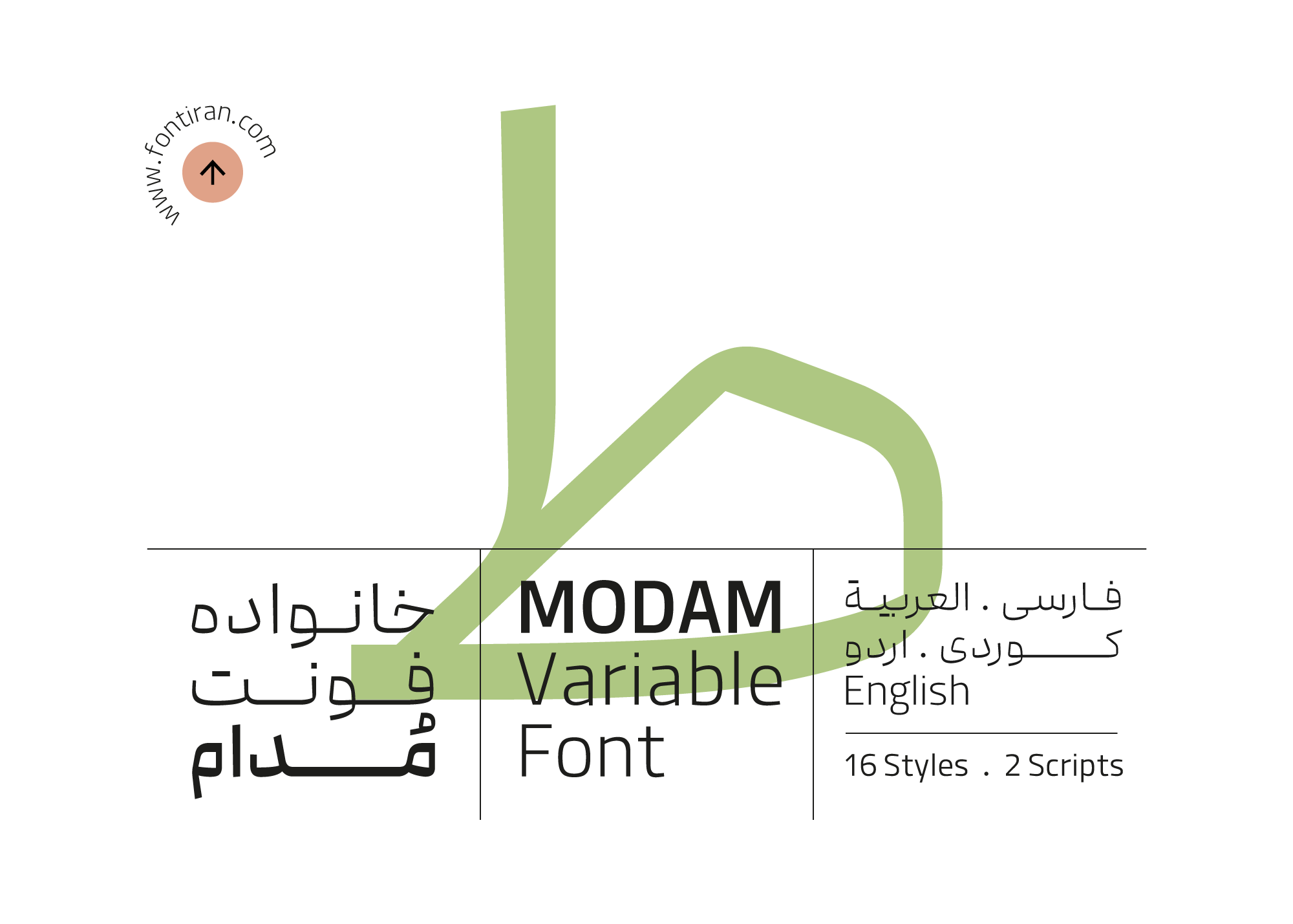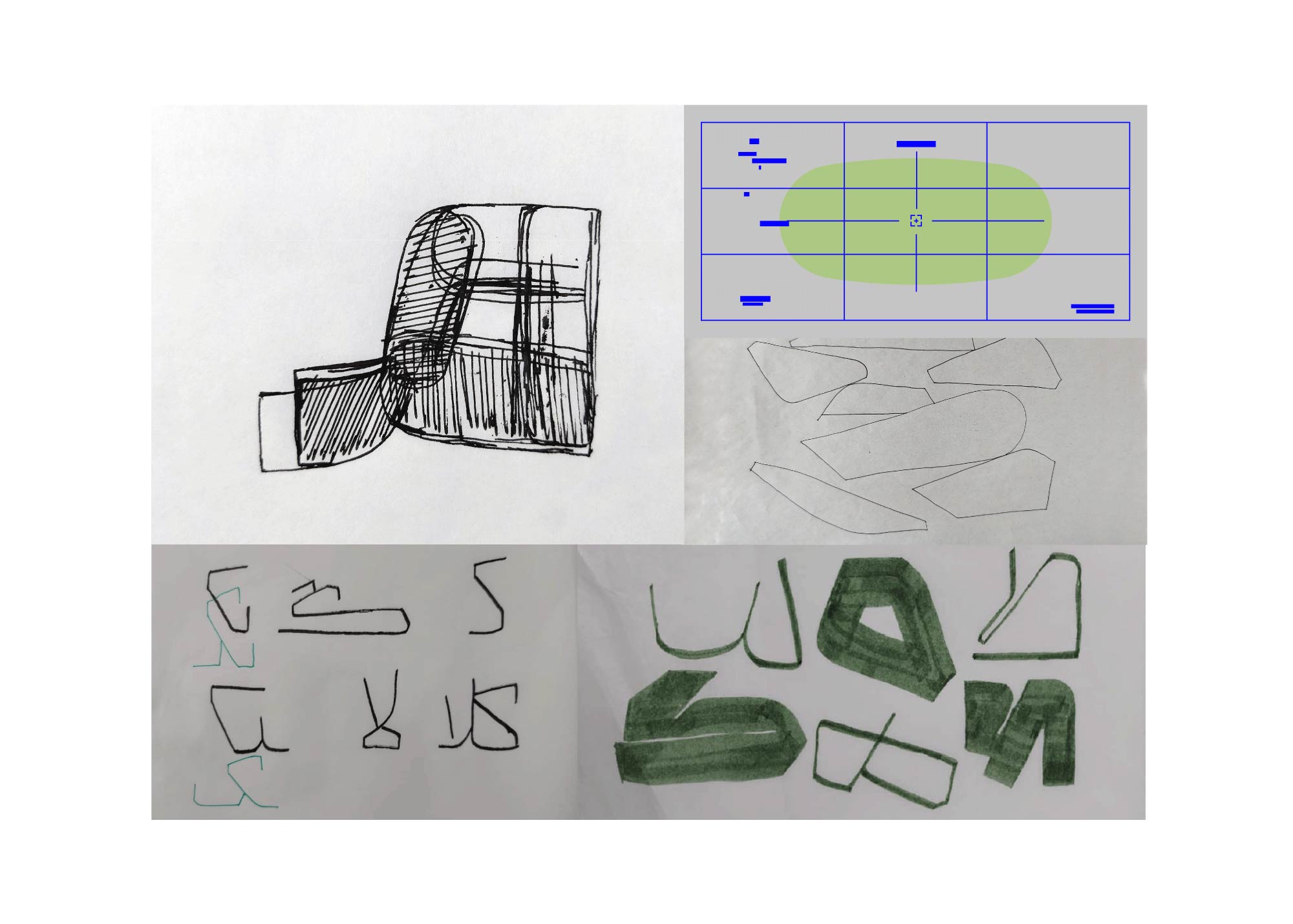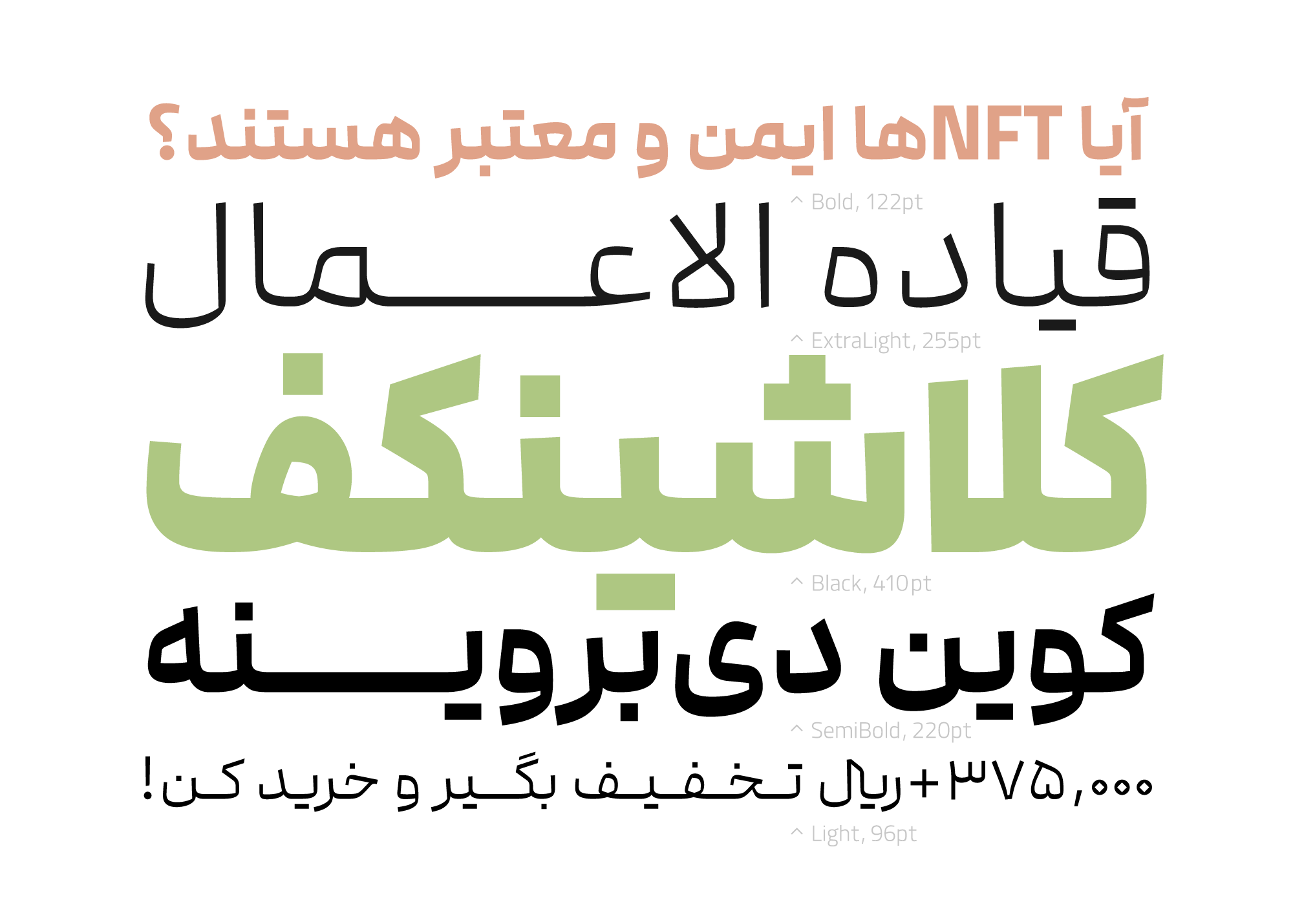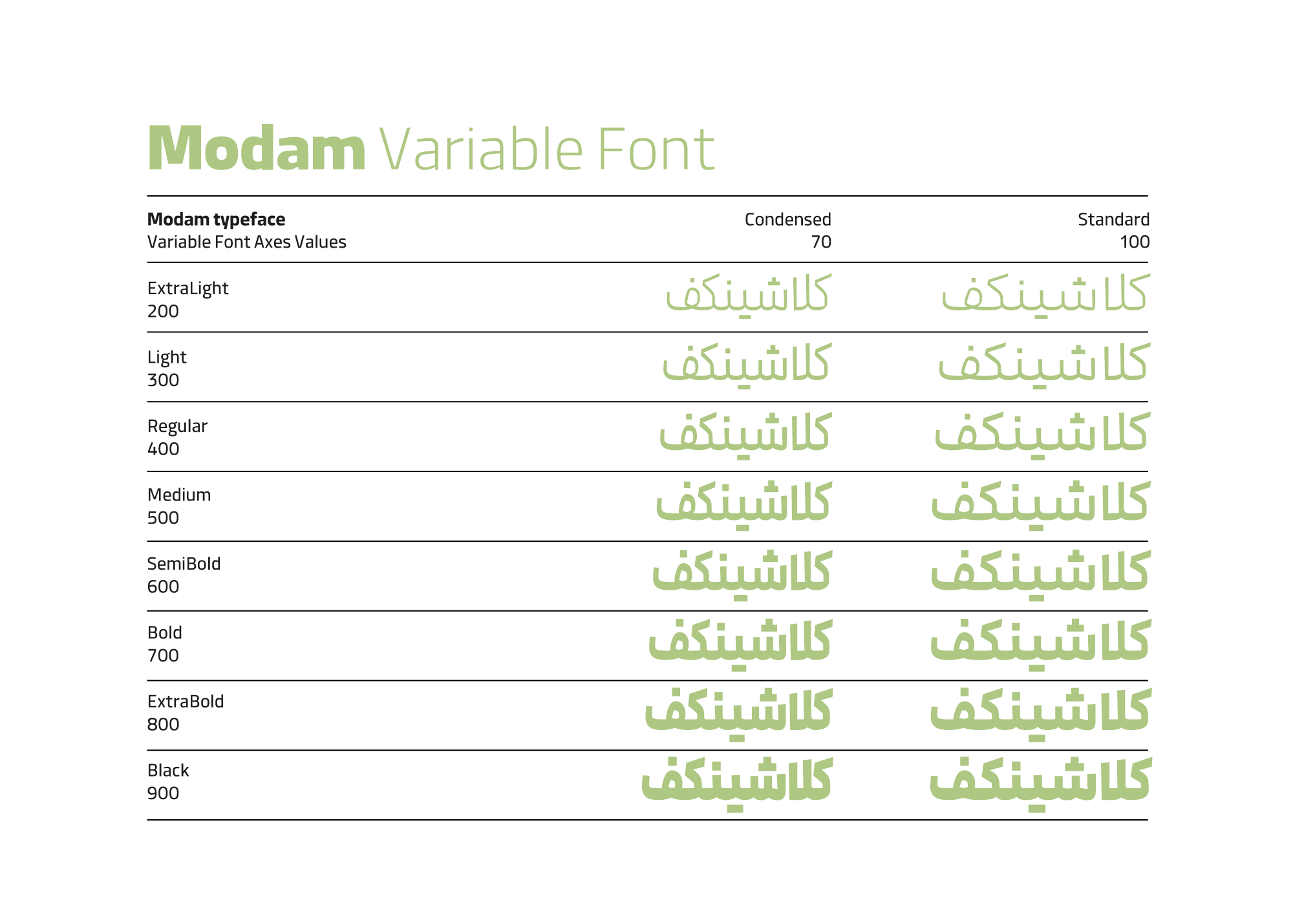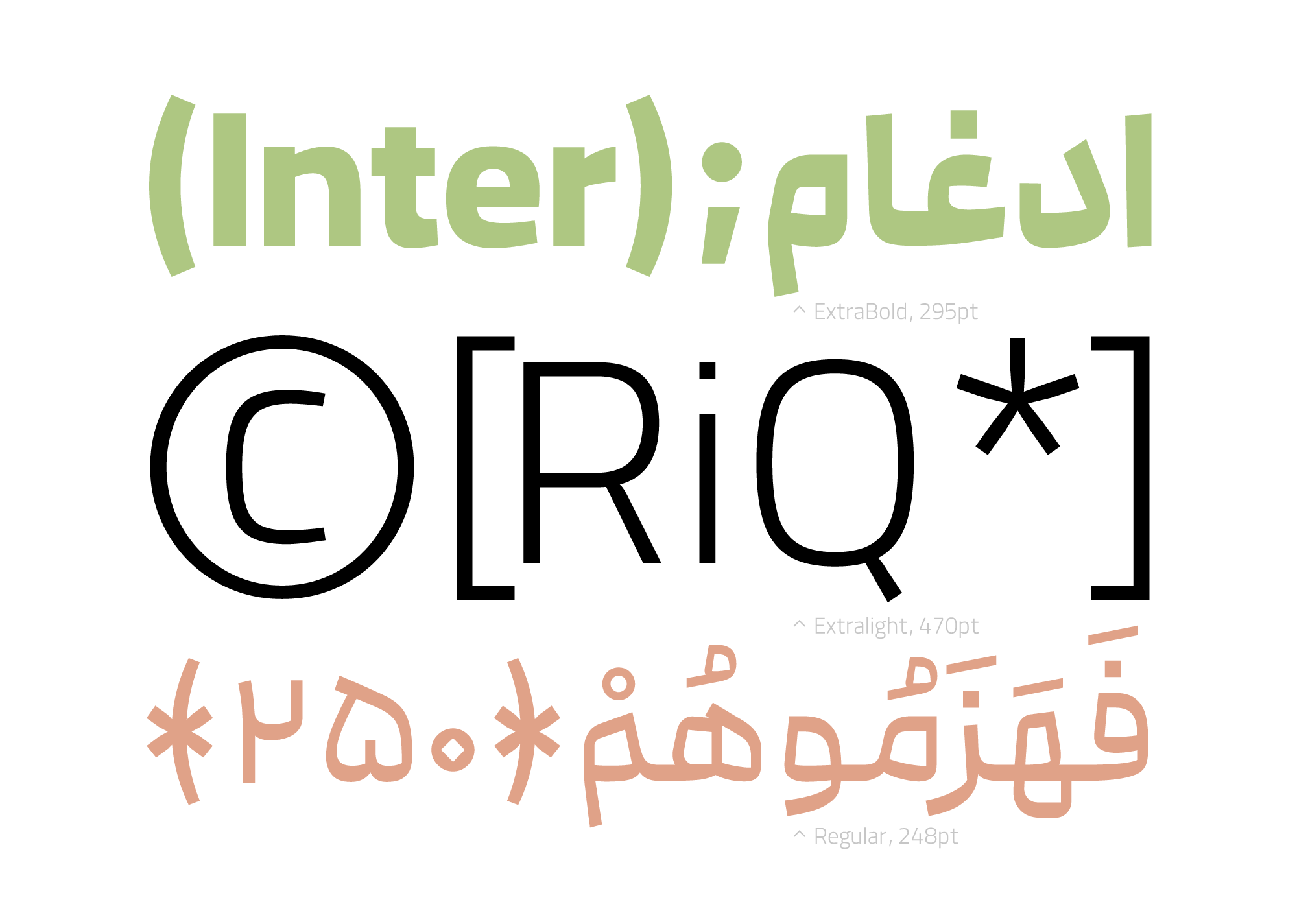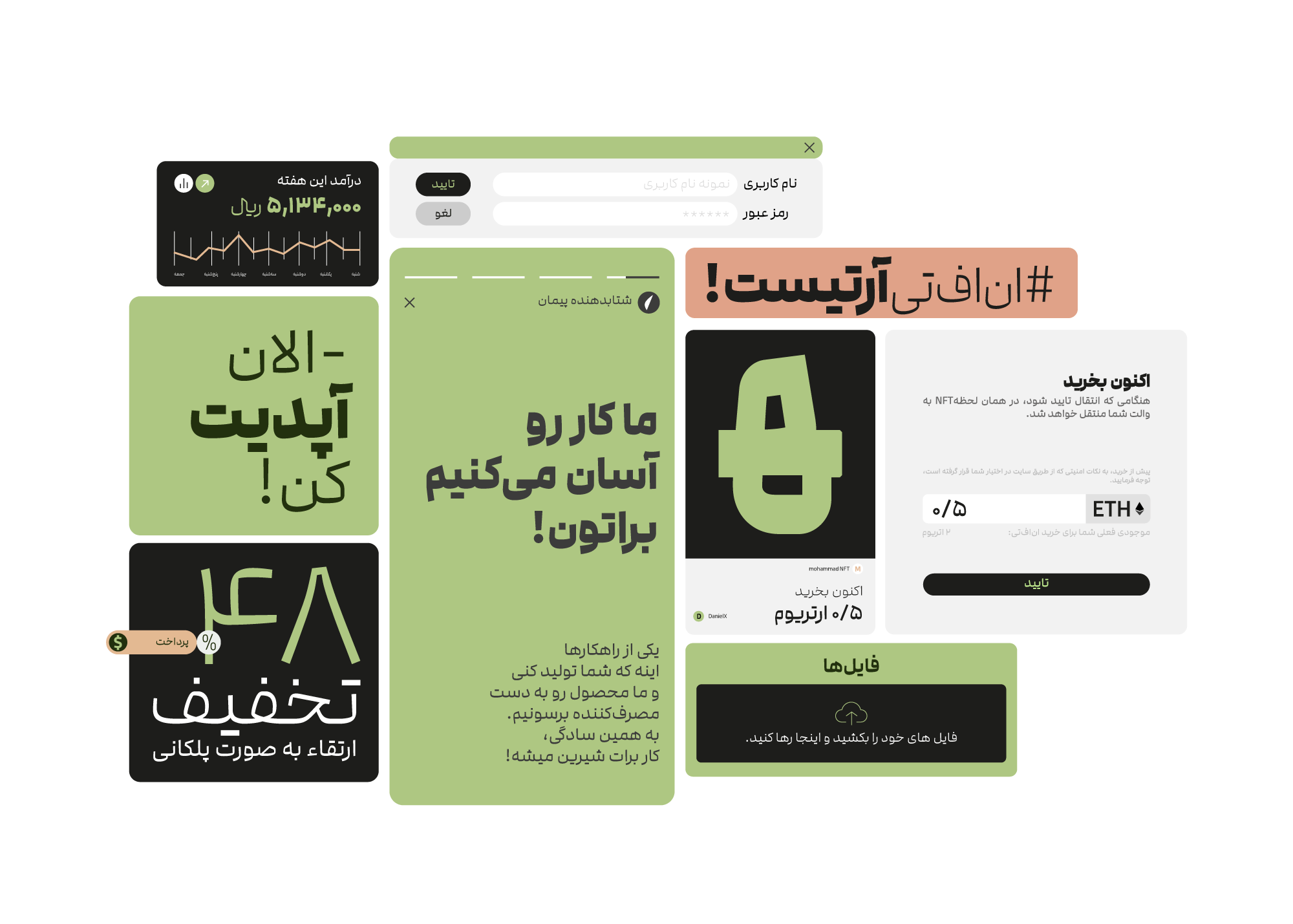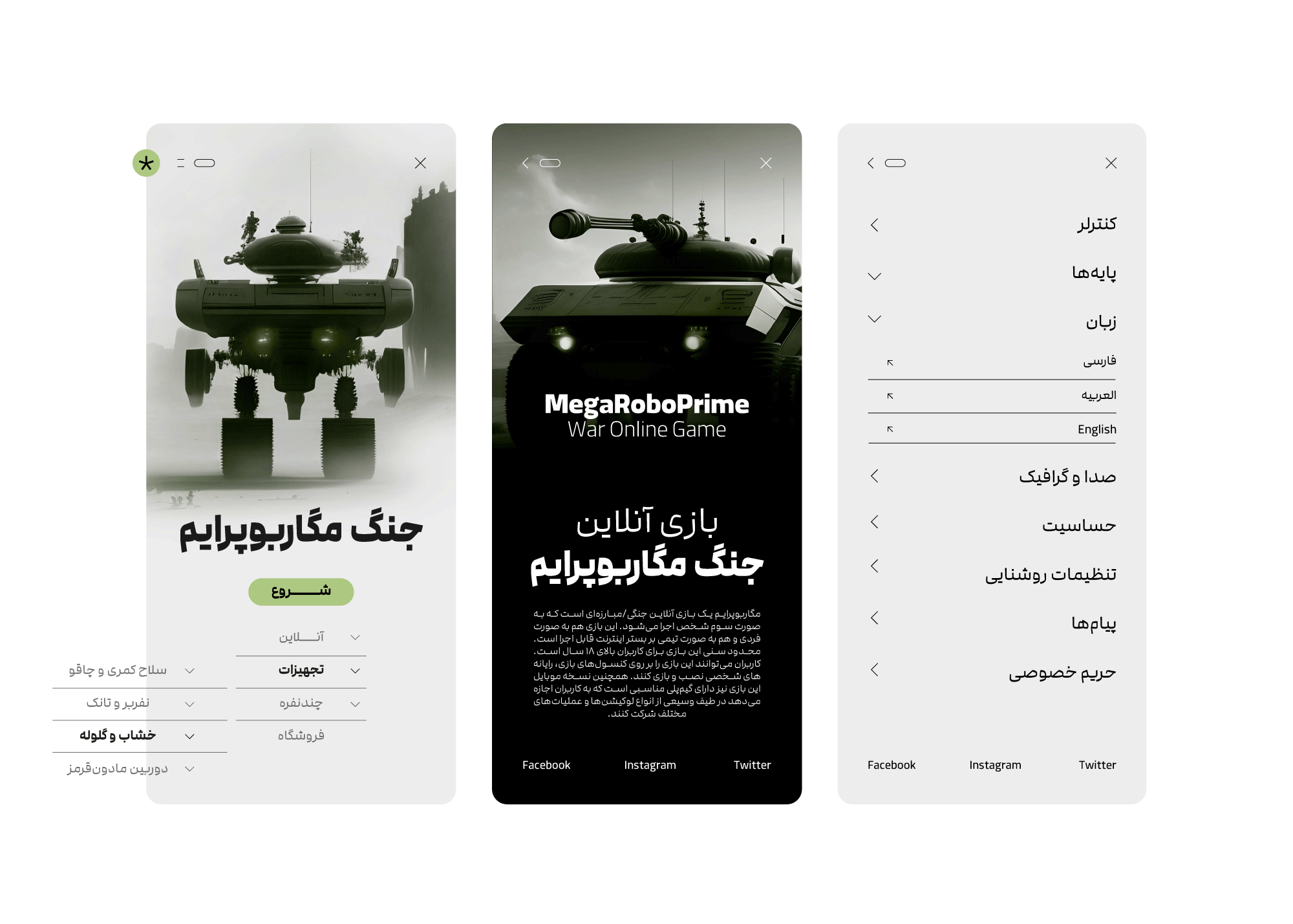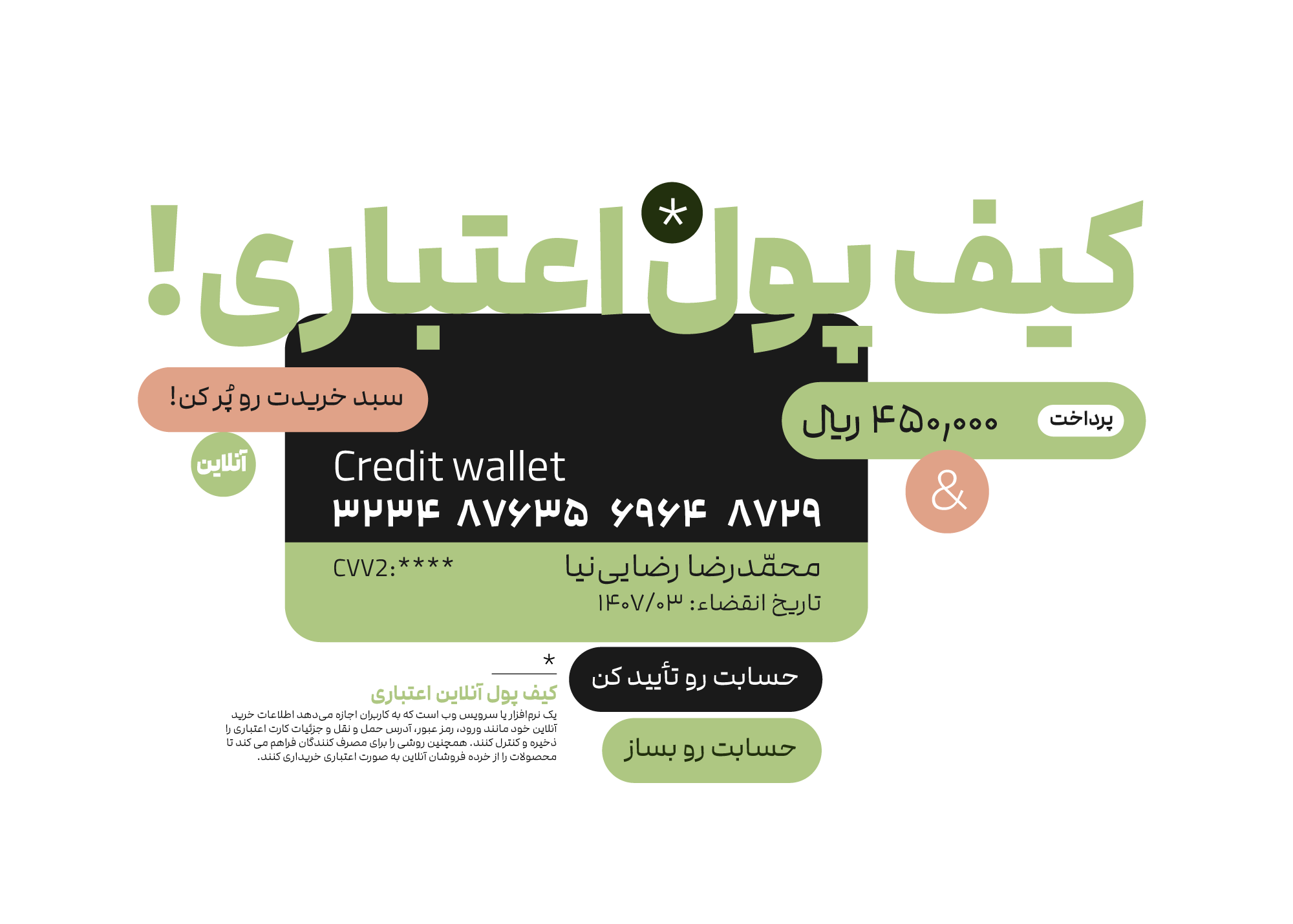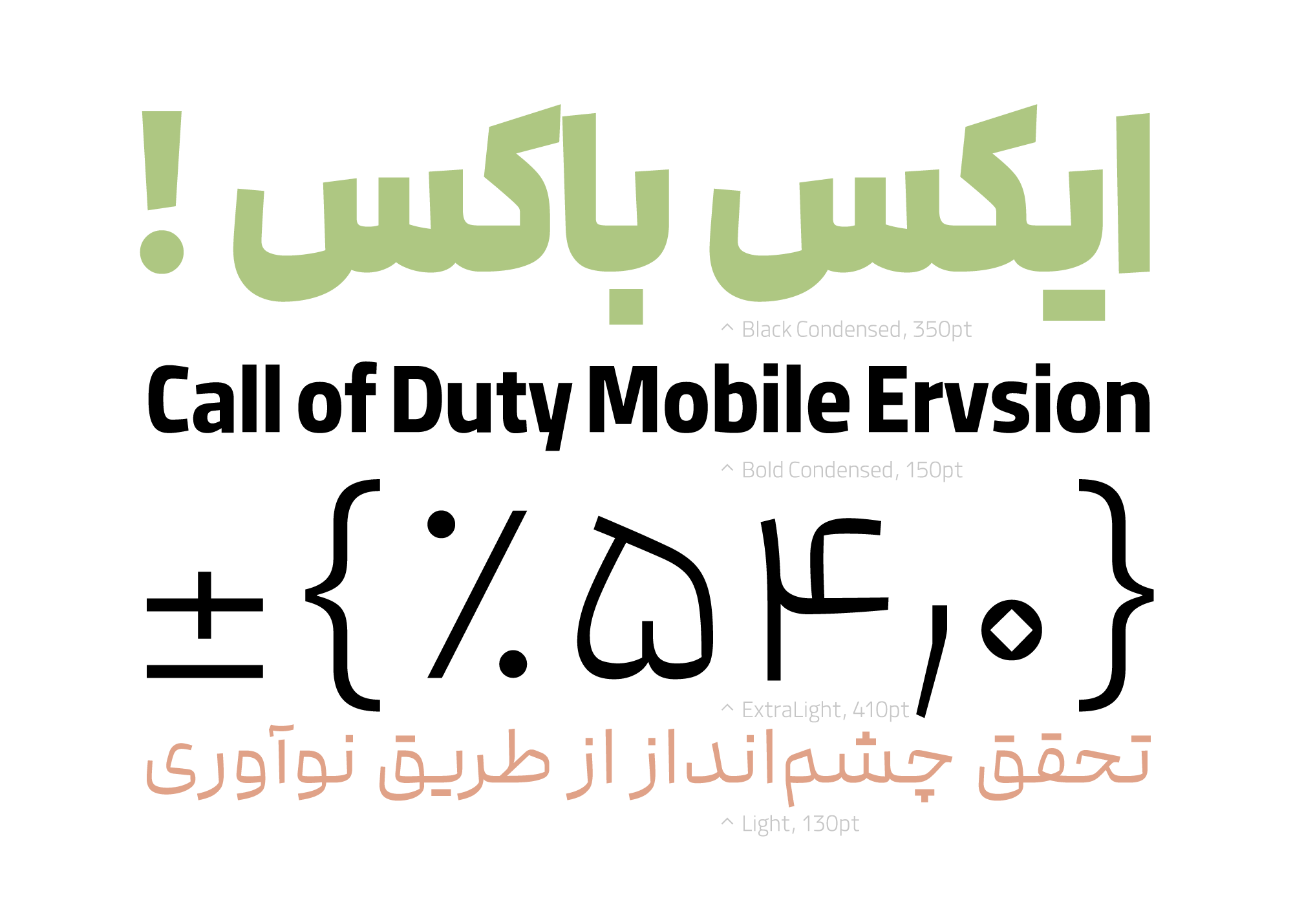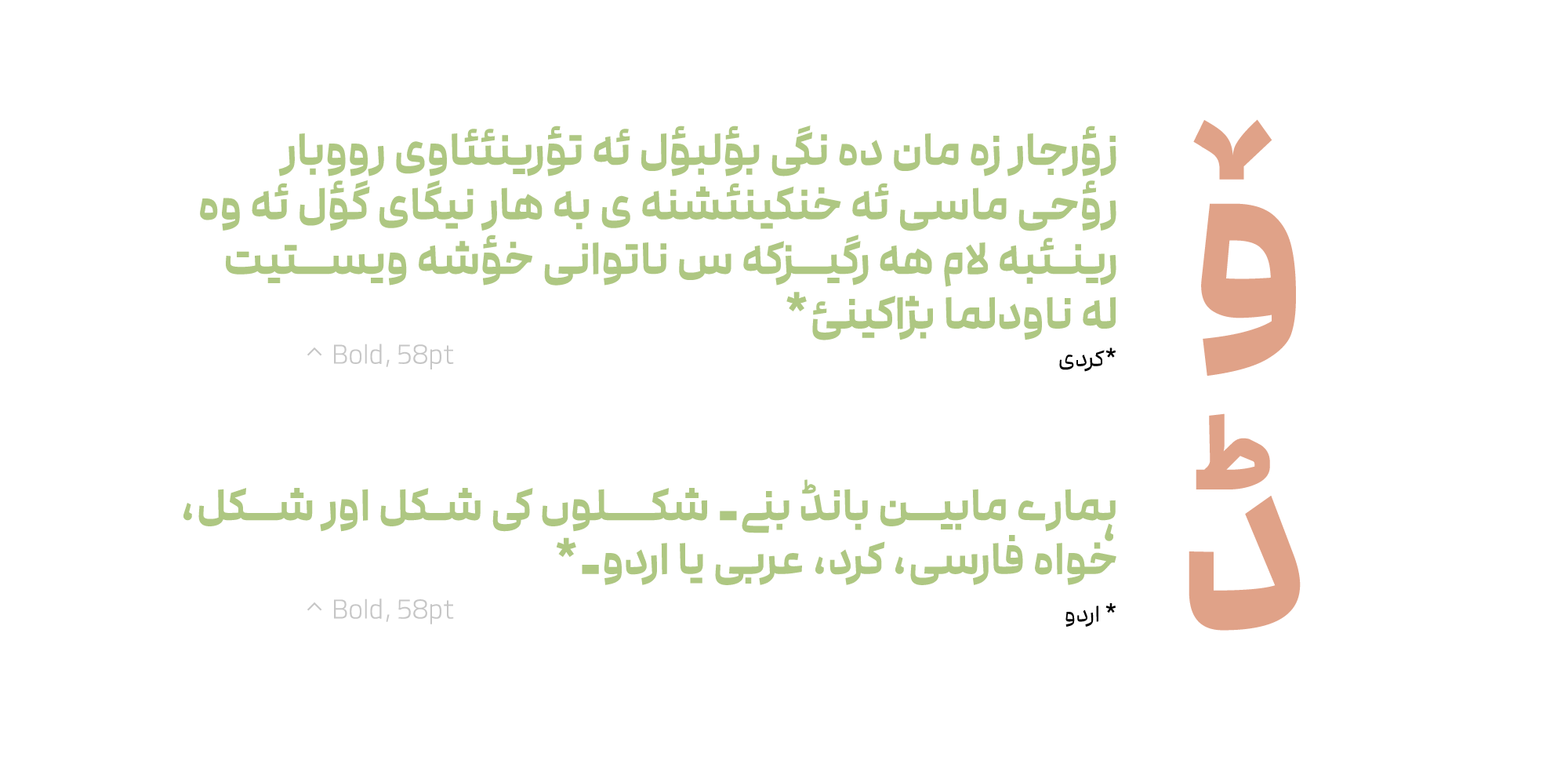
فونت مدام از زبانهای فارسی، عربی، کردی، اردو و انگلیسی پشتیبانی میکند.
شکلگیری تایپفیس مُدام
یکی از دغدغههای من، طراحی تایپفیسهایی برای استفاده در فضای بازیهای دیجیتال و مدیومهایی در بستر وِب است. در پاییز ۱۴۰۰ که در کلاسهای آنلاینِ طراحی تایپِ استادم دامون خانجانزاده شرکت کردم، این فکر و دغدغهام را با ایشان در میان گذاشتم و ایشان بسیار استقبال کردند.
از میان مباحث گستردهی تئوری، تجزیه و تحلیلهای فرمی و بصری، تحلیل کانسپ، اتودهای فرمی و در نهایت اتودهای طراحی حروف، این تایپفیس ساخته شد که آن را «مُدام» نام نهادم. فرآیند مطالعات، تحقیق و طراحی این تایپفیس و آنچه در این مسیر از جناب ایشان آموختم را بهصورت مقالهای جداگانهای منتشر خواهم کرد.
آشنایی با فونت مُدام
تایپفیس «مُدام» دارای ساختاری ساده، اندامی استخوانی و فضاهای منفی باز است. این تایپفیس به دلیل روحیهی نمایشی و درجهی بالای تناسبات هندسی آن، برای تیتر و متنهای کوتاه و نیمه بلند مناسب است.
استارتاپها، طراحان و توسعهدهندگان بازی، وب و اپلیکیشن میتوانند مهمترین کاربران این تایپفیس باشند.
۸ وزن + استایل فشرده
فونت مُدام دارای ۸ وزن از نازک تا تیره است که میتواند تمام نیازهای پروژههای طراحی گرافیک و هویتسازی را برطرف نماید.
از آنجایی که در اکثر بازیها -در کنار خوانایی و خواندنی بودن نوشتار- نیاز به هیجان و انرژی همراه با تصویر در حروف نیز به چشم میخورد، همچنین محدودیتهایی که در نرمافزارها (باکسها و دکمهها) و یا ستونهای صفحهآرایی وجود دارد، استایل فشردهی این فونت نیز طراحی شد. برای فشردهسازی، تلاش شده است فرم حروف همچنان حفظ شود و این فشردهسازی در آنها اعوجاج ایجاد نکند. همچنین در این تغییر میزان فشردگی، ضخامتِ حروف نیز تا حد امکان ثابت مانده است؛ یعنی مثلاً ضخامتِ حروف در وزن رگولار با وزن رگولارِ فشرده یکسان است و فقط فرم حروف فشرده شده است.
وریبل فونت مُدام
در بستهٔ حرفهای فونت مدام ۱۶ فونت (۸ وزن + استایل فشرده) را میتوانید در قالب یک فونت متغیر استفاده کنید. فونت متغیر بهترین گزینه برای استفاده در طراحی وب است. کم حجم است، لود صفحه شما را سریعتر میکند و بدون محدودیت میتوانید از همه وزنها و استایلها استفاده کنید. از فونت متغیر همچنین میتوانید در نسخههای جدید فتوشاپ، ایلاستریتور و ... استفاده کنید.
وریبل فونت مدام دارای ۲ محور تغییر وزن و محور تغییر عرض (فشرگی) است.
پشتیبانی از زبان عربی و انگلیسی، اردو و کردی
فونت مُدام برای زبان فارسی و عربی طراحی شده است و زبانهای اردو، کردی و انگلیسی را نیز پشتیبانی میکند.
اعداد همعرض!
یکی از امکاناتی که در فونت مُدام در نظر گرفته شده است، استفاده از Tabular lining است. با فعالسازی این ویژگی در نرمافزارهای گرافیکی مانند ایلاستریتور و فوتوشاپ، میتوانید بدون استفاده از جدولکشی، اعداد را به صورت زیرِ هم بنویسید.